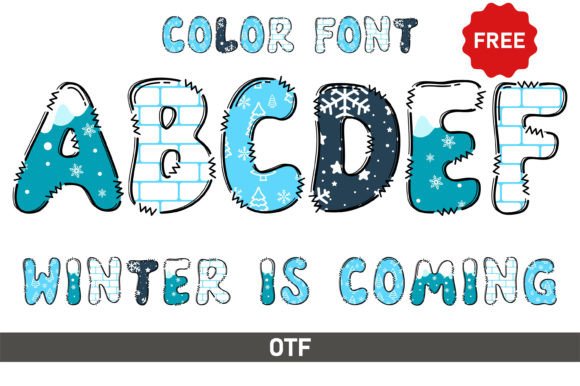
Winter is Coming
Winter is Coming – Resenha Completa e SEO‑Friendly
Se você está à procura de uma obra que combine mistério, suspense e uma ambientação gelada que prende a atenção do leitor, Winter is Coming é a escolha certa. Neste ulasan detalhado, vamos analisar enredo, personagens, estilo de escrita e o que torna este livro indispensável para fãs de thrillers e dramas psicológicos.
Enredo – O que acontece em “Winter is Coming”?
Ambientado em uma pequena cidade coberta de neve, o romance segue a investigadora Lara Mendes enquanto ela desvenda uma série de desaparecimentos misteriosos. Cada pista leva a um segredo antigo que ameaça congelar o futuro da comunidade. A narrativa alterna entre passado e presente, criando uma trama intrincada que mantém o leitor “preso” até a última página.
Personagens – Profundidade e empatia
- Lara Mendes: protagonista forte, inteligente e vulnerável – uma combinação que gera identificação imediata.
- Victor Alencar: o antagonista enigmático, cujas motivações são reveladas gradualmente, aumentando o suspense.
- Os moradores da cidade: cada um representa um arquétipo social, contribuindo para a atmosfera claustrofóbica.
Estilo de escrita – Um toque artístico
O autor utiliza fontes tipográficas que lembram desenhos infantis e cartazes divertidos — uma escolha curiosa que cria contraste com o clima sombrio da história. Essa mistura “playful” e “artistic” reflete-se nas descrições vívidas de flocos de neve, reforçadas por uma tipografia que, assim como nas children’s books, torna a leitura mais envolvente.
Aspectos técnicos – Compatibilidade e design
Conclusão – Vale a pena ler?
Com uma trama intrigante, personagens memoráveis e um design tipográfico que surpreende, Winter is Coming se destaca como leitura obrigatória em 2026. Seja para quem busca um thriller intenso ou para designers que apreciam fontes criativas, este livro oferece algo para todos.